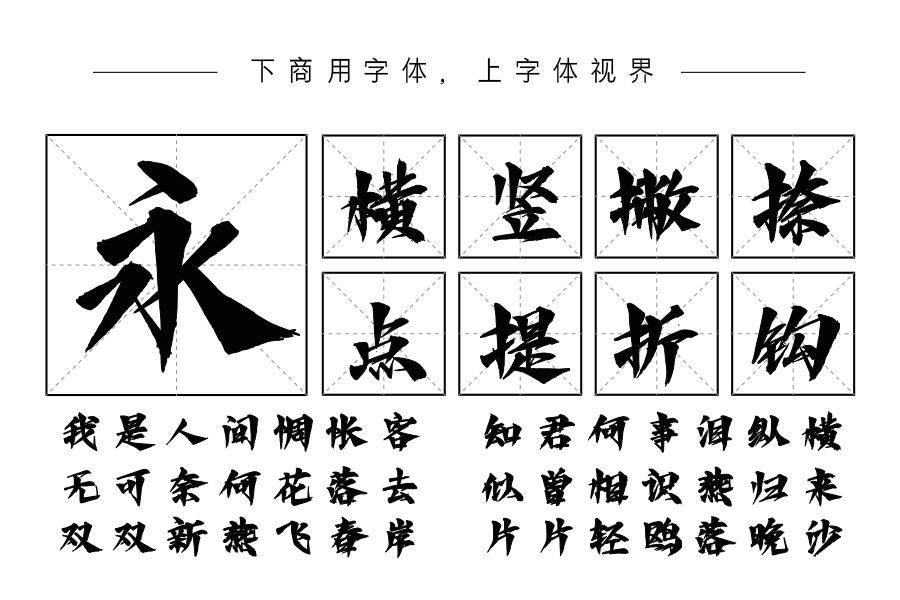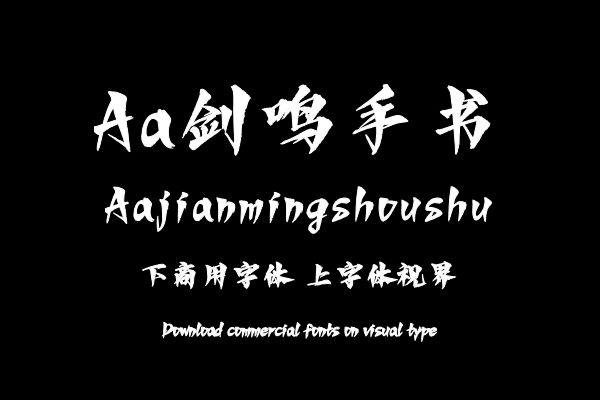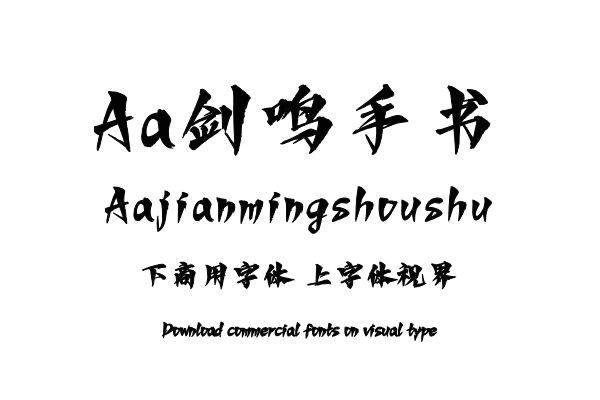
以突出笔锋的锋锐来设计一款标题手书字体。将传统书法的轻重变化归纳为三角形笔画,设计一款起收笔锐利、粗细变化强的书法字体。购买须知:“下载服务费”与“字体VIP”所获得字体 仅用于个人非商用, 商用请联系付费授权。本字体为电脑用字,手机没有root权限不支持直接手机换字(手机如何root,请自行百度搜索教程)。购买前请先 了解清楚后再付款 ,字体为虚拟产品无法回收 一旦购买不支持退款。